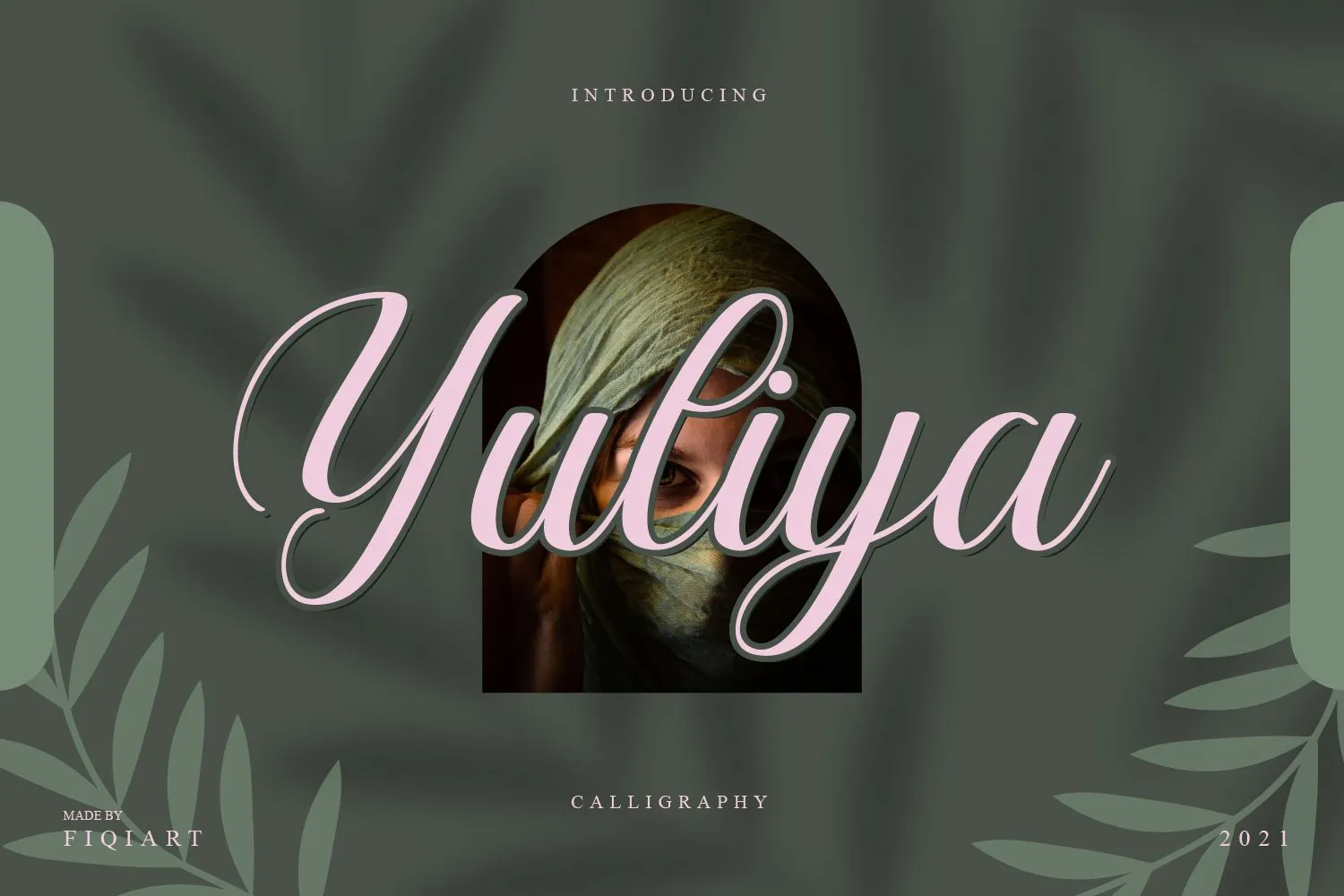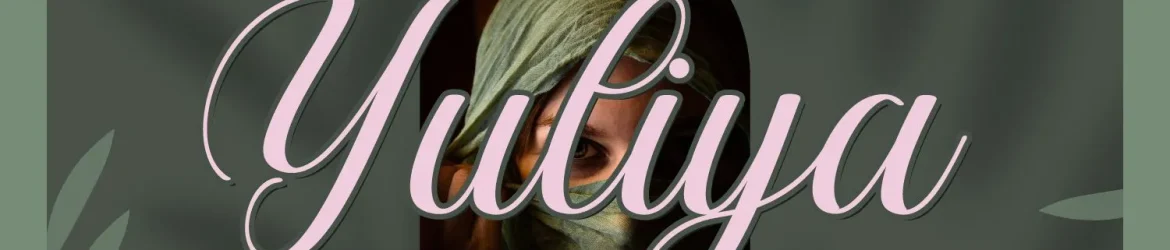
Yuliya Font – Download Grátis
A fonte Yuliya é perfeita para aqueles apaixonados por arte elegante e delicada. Seus traços suaves e fluídos são ideais para criar convites de casamento impressionantes, arte de papel impressa sofisticada, postagens sociais chamativas e muito mais. Para quem busca adicionar um toque especial a seus projetos digitais, Yuliya é uma ótima escolha. Seja em uma pequena nota pessoal ou no design de uma publicação de mídia social, o estilo delicado e elegante da fonte Yuliya trará um ar único à sua produção. Sua elegância fluente a torna perfeita para decorar qualquer projeto que você está trabalhando. Com certeza vai deixá-lo apaixonado por seu estilo inconfundível.
Designer: fiqiart